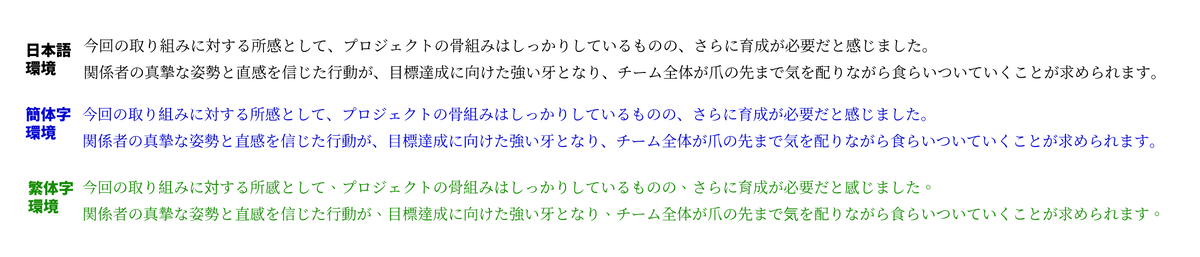
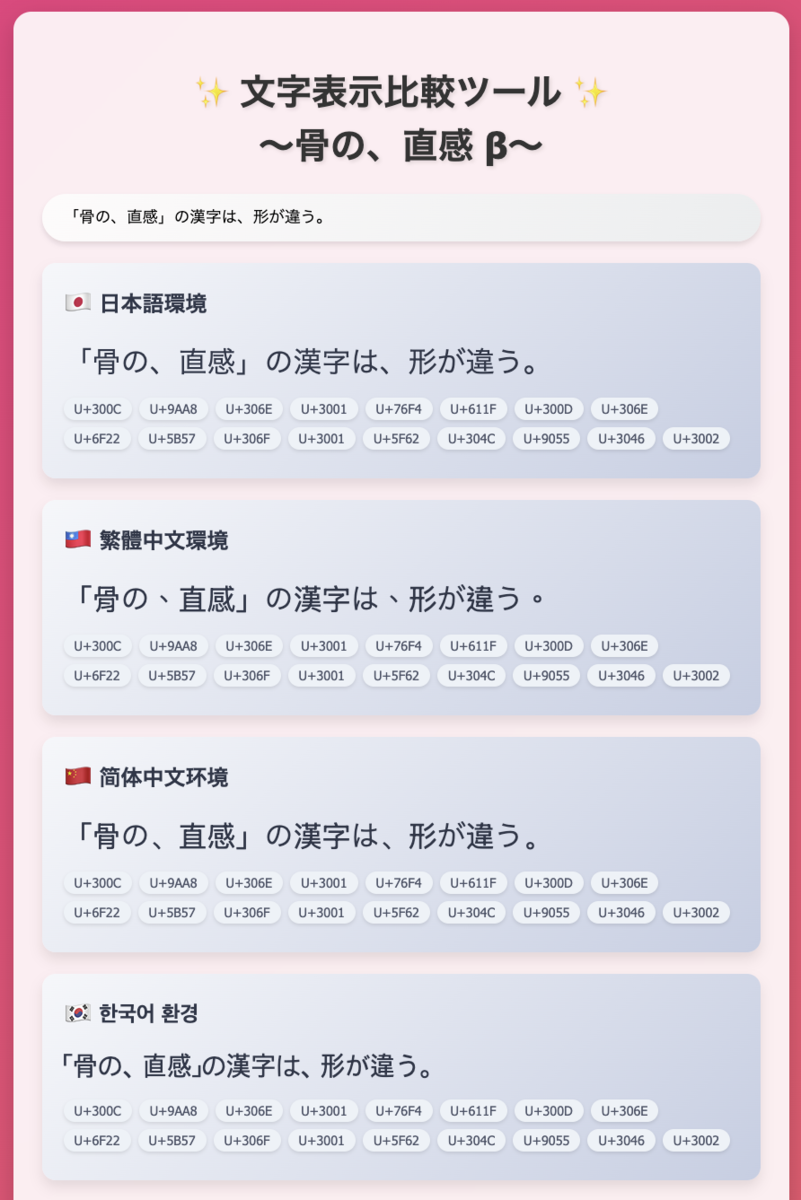
インバウンドや海外進出、越境ECにおけるデザイン品質向上をサポート!多言語対応デザインの品質を支えるWebアプリ「文字表示比較ツール ~骨の、直感~」
台湾でマーケティング業を行う「台灣琉球黃豆冰有限公司 DJ KINAKOMOCHI ICE Ltd. 」は、誰でも会員登録不要・無料で利用できるWebアプリ「文字表示比較ツール ~骨の、直感~」β版の提供を2024年10月31日から開始した。
2024年、東アジア圏からのインバウンドが過去最高を記録している。
多くの企業やブランドが、年末商戦に向け中国、台湾、韓国からの訪日観光客に向けた多言語対応を強化することで新たなビジネスチャンスを模索しており、既にアジア各国に進出している企業も多く見られる。
日本語・繁体字中国語・簡体字中国語・韓国語における文字形状の差異をリアルタイムで確認できるWEBアプリを活用することで、意図せぬブランドイメージが損なわれるリスクを軽減する。
デザインミス防止に繋がるリアルタイムで字形をチェック可能なWebアプリ「文字表示比較ツール ~骨の、直感~」
Webアプリ「文字表示比較ツール ~骨の、直感~」では、ブラウザ上で文字を入力するだけで、日本語・繁体字中国語・簡体字中国語・韓国語の各環境で異なる文字形状を即座に確認できる。
これにより、従来必要だった複数デバイスやフォントの準備という煩雑な工程を削減し、多言語デザイン確認の効率を劇的に向上させる。
マーケティング資料、製品パッケージ、観光情報発信などで多言語対応が求められる場面においても、的確なデザインが実現できる。
「文字表示比較ツール ~骨の、直感~」が解決する課題
「文字表示比較ツール ~骨の、直感~」は、異なる言語環境で文字の形状が変わる「CJK統合漢字問題」に対応するために開発された。
同じ文字データでも、日本語、繁体字中国語、簡体字中国語などの言語設定によって字形が微妙に異なるケースが多く見られる。
例えば、日本向けのデザインに中国や台湾の字形を使用すると、プロフェッショナルな印象が欠け、ブランドの信頼性が損なわれる恐れがある。
逆に、中国・台湾向けのデザインに日本の字形を使用する場合も同様の課題が発生し、企業イメージに悪影響を与えかねない。
本アプリは、これらの字形差異をリアルタイムで確認することで、タイポグラフィデザインの品質向上をサポートし、東アジアの複数言語に対応したプロフェッショナルな成果物の作成に寄与。
東アジアへの対応強化、ビジネスチャンスを逃さないために、いまこそ必要なツール「文字表示比較ツール ~骨の、直感~」
2024年、東アジア圏からのインバウンドが過去最高を記録している。
多くの企業やブランドが、中国、台湾、韓国からの訪日観光客に向けた多言語対応を強化することで新たなビジネスチャンスを模索しており、既にアジア各国に進出している企業も多く見られるが、字形の違いを理解せず不適切なデザインが生まれるケースは、企業規模や官民を問わず見受けられる。
字形の違和感が品質の信頼性低下を招き、日本の強みである「高品質」なイメージが損なわれる恐れがある。
こうした問題を防ぐためにも、字形差異を容易に確認できる本ツールの活用が期待されている。
同じ文字でも見え方が違う「CJK統合漢字問題」
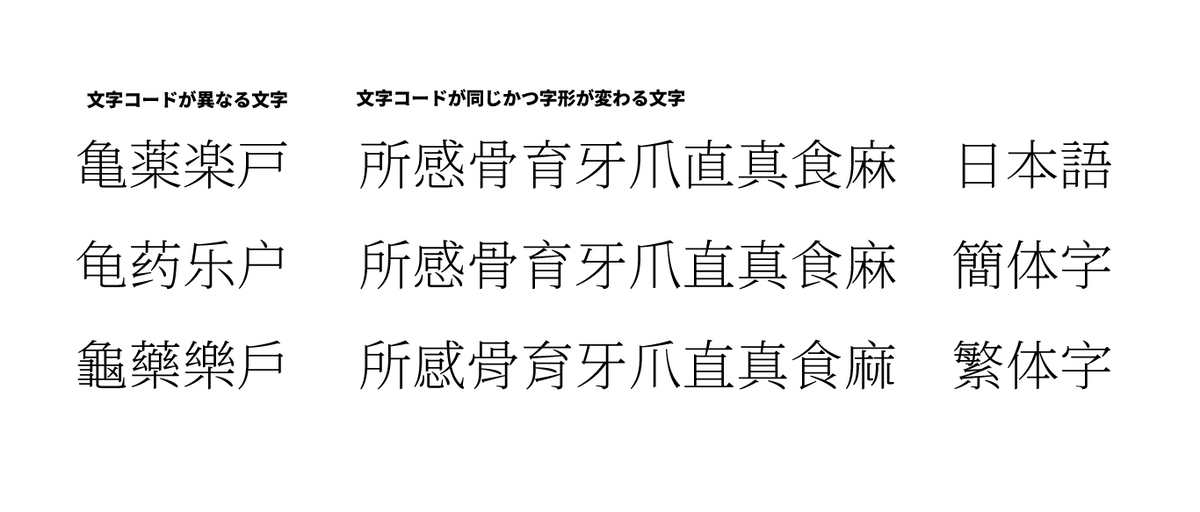
東アジアで使用される漢字には、日本語、繁体字中国語、簡体字中国語、韓国語でそれぞれ異なる字形が存在するものの、これらはUnicodeで同じコードポイントに統合されているため、環境やフォント設定によって見た目が異なる「CJK統合漢字問題」が発生している。
ここで問題としているのは、日本語の「薬」、繁体字中国語の「藥」、簡体字中国語の「药」のように文字そのものが異なり、Unicode上で別のコードが割り当てられているケースではない。
この場合、文字コードが異なるため、誤表示の問題は起きにくいの。
実際に厄介なのは、たとえば「骨」のように、日本語、繁体字中国語、簡体字中国語で同一のUnicodeコードポイントが割り当てられているにもかかわらず、見た目が異なる漢字。
日本語では和字形、繁体字では繁体字形、簡体字では簡体字形が適用され、設定に応じて異なる見た目で表示されることがあり、これが予期せぬ違和感を生じさせる要因となっている。
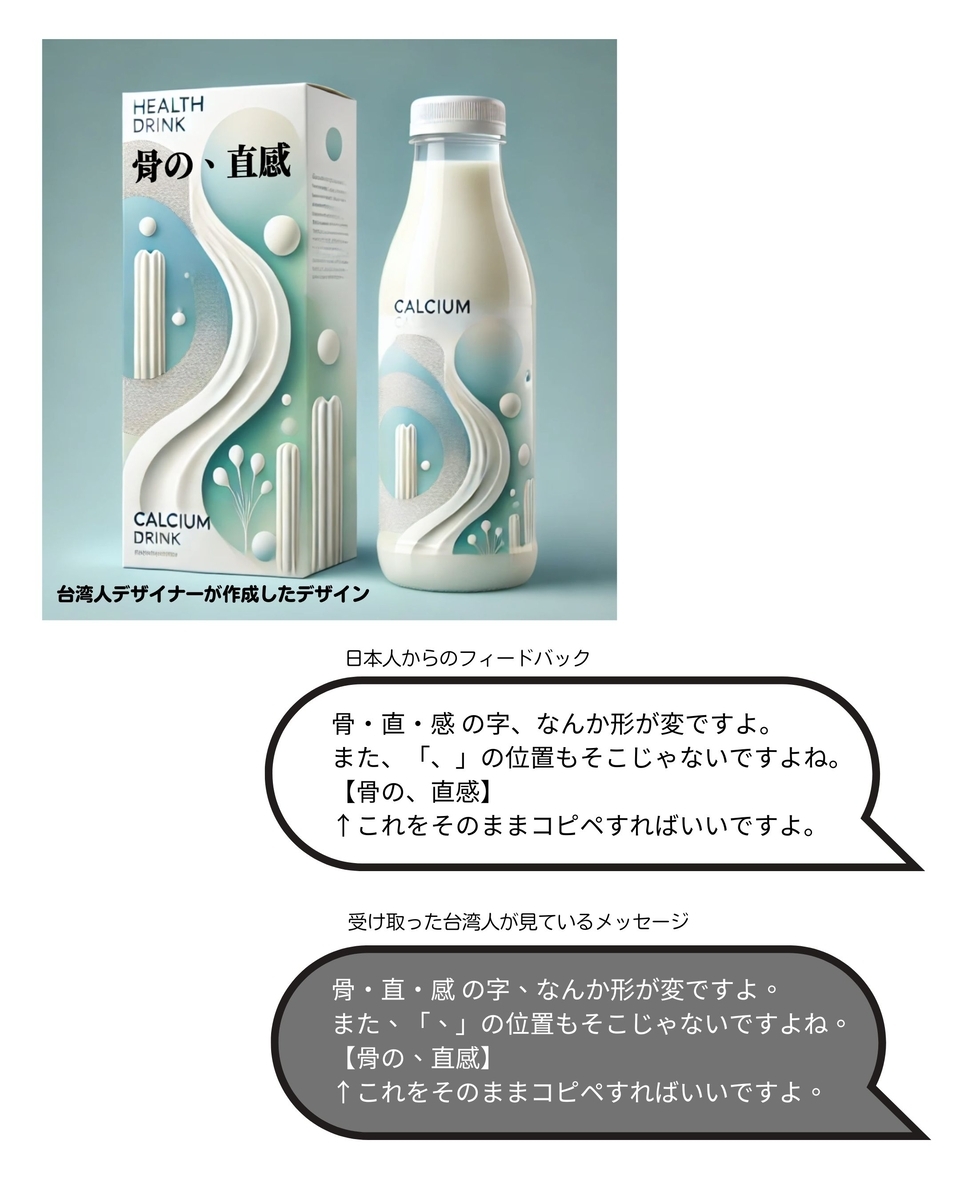
テキストメッセージでフィードバックを送っても、相手の環境では伝わらない。
この問題は、日常のテキストコミュニケーションにも影響を及ぼしている。
例えば、Aさんが送信した文字が日本語の字形で見えていても、Bさんが異なる言語設定で確認すると別の字形で表示される可能性があるため、双方が気づかないまま異なる字形を認識しながらやり取りしてしまうことが多く、仮に違いに気づいて指摘しても、環境の違いにより共通の理解が得られないことも珍しくない。
また、句読点の位置にも言語環境による違いが生じます。日本語環境では句読点の「。」や「、」が行の下部に配置されるのに対し、台湾など繁体字中国語の環境では中央に配置されることが多く、タイポグラフィ全体の質に影響を与え、デザインや文章表現の統一感を損ねる恐れがある
。
文章の場合でも、じっくり見比べると違いがある。
多くのデザイナーは、こうした細かな字形の違いに精通しているわけではないため、校正時に誤りを見逃してしまうことも少なくない。
「文字表示比較ツール ~骨の、直感~」は、デザインのプロフェッショナルが言語の専門知識を持たずに、各環境での正確な字形を確認でき、クリエイティブなプロセスを支える重要な役割を果たしている。